폰트 두 개 꼭 써야 할까? 단일 패밀리로 충분한지 판단하는 법
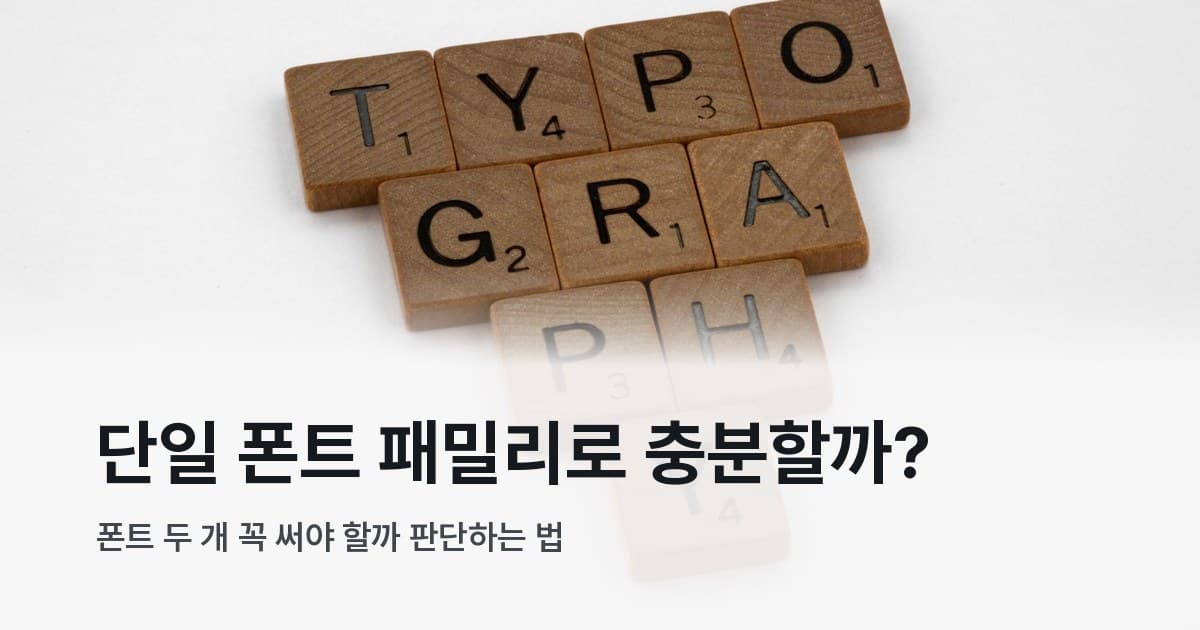
디자인 커뮤니티 어디서나 폰트 조합, 폰트 페어링 추천 글은 넘쳐난다. "제목용 + 본문용 두 가지는 기본"이라는 말이 공식처럼 굳어진 분위기다. 그런데 막상 두 폰트를 섞으면 오히려 산만해지거나 어디에 무엇을 써야 할지 헷갈려서 작업 시간만 늘어났다는 경험, 한 번쯤 있지 않나요.
두 번째 폰트가 문제를 해결해줄 것 같지만, 사실 그 상황의 원인이 폰트 가짓수가 아닌 경우가 꽤 많다. 폰트 조합을 늘리기 전에 지금 쓰는 패밀리의 굵기 단계부터 제대로 활용하고 있는지 확인하는 게 순서다. 이 글은 두 번째 폰트를 쓰기 전에, 그게 정말 필요한 상황인지 먼저 걸러내는 기준을 다룬다.
두 번째 폰트가 필요 없다는 신호 세 가지
생각보다 많은 작업이 단일 패밀리로 해결된다. 아래 중 하나라도 해당하면, 두 번째 폰트 없이도 충분한 상황이다.
① 쓰는 폰트의 굵기 단계가 3개 이상이다 타이포그래피 교육 플랫폼 Pimp my Type도 같은 패밀리 내에서 굵기 단계만으로 명확한 시각 구분을 만들 수 있다고 강조한다. 크기·굵기·색상 대비 세 가지가 맞아떨어지면, 폰트 한 종류로도 화면이 충분히 정돈된다. weight 선택지가 Light·Regular·Bold 이상이라면 대부분의 위계 요구사항을 커버할 수 있다.
② 텍스트가 짧거나 슬라이드 단위로 읽힌다 SNS 카드, PPT, 포스터처럼 텍스트 영역이 짧고 한눈에 읽히는 구조라면 폰트 혼용의 효과가 거의 없다. 오히려 두 폰트가 좁은 면적에서 충돌해 산만해지는 경우가 더 많다.
③ 웹이나 앱에서 로딩 속도가 중요하다 폰트 종류가 늘수록 초기 렌더링 속도에 직접 영향을 준다. 폰트 파일을 하나만 로드하는 것만으로 페이지 속도 최적화에 유리하고, 같은 설계 DNA에서 나온 글자들이라 따로 조율하지 않아도 자연스럽게 어울린다. 웹 성능을 챙겨야 하는 프로젝트라면 폰트 조합보다 단일 패밀리를 우선 검토하는 게 합리적인 선택이다.
단일 패밀리로 충분한지 판단 체크리스트
두 번째 폰트를 검토하기 전에, 아래 항목을 먼저 확인해보자. 체크 항목 대부분에 해당한다면 단일 패밀리로 충분할 가능성이 높다.
- 현재 쓰는 폰트의 weight가 Light·Regular·Bold 이상 3단계 이상 존재한다
- 크기·굵기·색상 대비만으로 원하는 위계 구분이 가능하다
- 텍스트 분량이 짧거나 슬라이드·카드 단위로 소비되는 콘텐츠다
- 웹/앱 프로젝트라 로딩 속도나 렌더링 최적화가 중요하다
- 브랜드 톤을 통일감 있게 유지하는 게 디자인 목표다
- 제목과 본문에 극단적으로 다른 개성이 동시에 필요하지 않다
- 영문 수치·UI 요소 비중이 크지 않아 한글 패밀리만으로 처리 가능하다
반면 체크 항목 중 아랫줄에 해당하는 게 많다면, 두 번째 폰트를 진지하게 검토해볼 타이밍이다. 이 체크리스트는 "정답을 주는 기준"이 아니라 작업 시작 전에 한 번쯤 멈춰서 생각해보게 하는 장치다. 무조건 두 종류를 쓰는 게 습관이 됐다면, 한 번은 이 순서대로 따져보는 게 도움이 된다.
그래도 두 번째가 필요한 경우는 언제인가
단일 패밀리가 기본 출발점이지만, 두 번째 폰트가 실제로 필요한 상황도 있다. 기준은 하나다. 역할이 다른 두 가지가 같은 화면에서 동시에 필요할 때.
- 제목은 강한 개성, 본문은 높은 가독성이 동시에 필요한데 같은 패밀리로 해결이 안 될 때
- 잡지·단행본처럼 세리프 본문 + 산세리프 제목을 명확히 분리해야 할 때
- 영문 UI 수치가 큰 비중을 차지해 한글 패밀리만으로는 숫자 가독성이 떨어질 때
반면 "굵기 1~2개뿐인 패밀리라 위계가 밋밋하다"는 문제는 두 번째 폰트를 더하기 전에 weight 단계가 충분한 패밀리로 교체하는 게 먼저다. Regular·Bold 두 가지뿐인 폰트에 두 번째를 붙여봐야 위계 문제는 그대로다.
폰트 조합을 결정할 때 한쪽이 아무리 예뻐도, 함께 놓였을 때 충돌하거나 어색하게 느껴진다면 그게 곧 "두 번째가 필요 없다"는 신호일 수 있다. 여러 weight를 갖춘 단일 패밀리 하나가 폰트 두 개를 억지로 붙이는 것보다 훨씬 더 일관된 결과를 내는 경우가 많다.
Pretendard를 단일 패밀리로 쓸 때 두 번째가 필요 없는 이유
단일 패밀리 전략이 현실에서 실제로 통하는 예로 Pretendard를 보자.
Pretendard는 GitHub(orioncactus/pretendard)에서 공식 배포하는 오픈소스 한글 폰트다. OFL-1.1 라이선스라 상업 사용·수정·재배포 모두 가능하고, 가변 폰트(Variable Font) 버전은 weight 45~920 범위를 연속으로 지원한다. 정적 버전은 아래 9단계를 제공한다.
| Weight 이름 | CSS 값 | 어디에 쓰나 |
|---|---|---|
| Thin | 100 | 장식·배경 레이어 텍스트 |
| ExtraLight | 200 | 서브 캡션·부가 정보 |
| Light | 300 | 본문 보조·긴 글 읽기 |
| Regular | 400 | 일반 본문 |
| Medium | 500 | 강조 본문·리드 텍스트 |
| SemiBold | 600 | 소제목(H3)·라벨 |
| Bold | 700 | 소제목(H2)·주요 강조 |
| ExtraBold | 800 | 대제목(H1)·히어로 텍스트 |
| Black | 900 | 포스터·최강 강조 포인트 |
9단계를 다 쓰라는 뜻이 아니다. 실제로는 3~4단계만 골라도 충분하다.
블로그 썸네일이라면 ExtraBold(800)로 메인 제목을 잡고, Bold(700)로 소제목, Medium(500)으로 리드 텍스트, Light(300)에 회색 계열 색상으로 캡션을 처리하면 된다. 네 단계만으로 위계가 명확히 완성되고, 두 번째 폰트를 불러올 이유가 없다.
PPT라면 더 단순하다. 타이틀(ExtraBold)·설명(Regular)·출처(Light) 세 단계면 슬라이드가 깔끔하게 정돈된다. SNS 카드는 핵심 메시지(Black 또는 ExtraBold)·부연(Regular) 두 단계면 충분하고. 단조롭지 않은 건 폰트 종류 덕분이 아니라 굵기 대비가 위계를 만들어주기 때문이다.
Pretendard처럼 weight 스펙트럼이 넓은 패밀리가 유독 UI 디자인·브랜드 가이드라인에 자주 쓰이는 이유도 이 때문이다. 한 패밀리 안에서 위계를 완성할 수 있으니, 굳이 폰트 조합 고민을 시작하지 않아도 된다.
작업 유형별 판단, 단일로 끝낼 수 있는가
아래 표는 작업 유형마다 "단일로 충분한 경우"를 먼저 보여준다. 두 번째 폰트 추가는 왼쪽이 안 될 때 검토한다.
| 작업 유형 | 단일 패밀리로 끝낼 수 있는 경우 | 두 번째를 고려하는 경우 |
|---|---|---|
| SNS 카드뉴스·썸네일 | weight 3단계면 충분 | 개성 폰트와 가독성 폰트를 동시에 원할 때 |
| PPT·프레젠테이션 | 슬라이드 단위라 단일이 깔끔 | 두 브랜드·채널이 공존하는 경우 |
| 웹사이트·앱 UI | 로딩 최적화와 통일성에 유리 | 영문 UI 수치가 큰 비중을 차지할 때 |
| 포스터·현수막 | 크기 대비로 위계 충분 | 장식체와 읽기체를 명확히 분리해야 할 때 |
| 긴 본문 편집물 | 굵기 3~4단계로 위계 가능 | 세리프 본문 + 산세리프 제목 구조일 때 |
| 브랜드 아이덴티티 | 패밀리 통일감이 강점 | 의도적 톤 분리가 브랜드 전략일 때 |
표의 오른쪽 열을 보면 패턴이 있다. 두 번째 폰트가 실제로 필요한 경우는 거의 다 처음부터 두 역할을 동시에 달성해야 하는 상황이다. 그 상황이 아니라면 먼저 단일로 시도해보는 게 낫다.
두 번째 폰트보다 먼저 확인할 것
폰트 페어링이 나쁜 게 아니다. 다만 "두 가지는 써야 한다"는 전제부터 시작하면 필요도 없는 복잡성을 스스로 끌어오게 된다. 폰트 조합이 많다고 디자인이 좋아지는 게 아니라는 점, 한 번쯤 새겨둘 만하다.
판단 흐름을 한 번만 바꿔보자.
- 현재 쓰는 폰트의 weight 단계부터 확인한다. Light·Regular·Bold 이상이 있는가?
- 크기·굵기·색상 대비만으로 원하는 위계가 만들어지는가? 만들어지면 거기서 멈춘다.
- 그래도 안 된다면 그때 두 번째 폰트를 검토한다. 단, 이유가 "굵기 부족"이라면 패밀리 교체가 먼저다.